글씨 교정하면 얼마나 달라질까 글씨가 삐뚤빼뚤해서 시험지 채점이 걱정됐던 적, 혹은 누군가에게 메모를 남기면서도 괜히 부끄러웠던 경험… 혹시 있지 않으신가요? 😅 많은 사람들이 성인이 되어서도 '내 글씨는 왜 이렇게 못생겼지?'라고 고민하곤 해요. 하지만 요즘은 다양한 글씨 교정 방법이 생기면서, 누구나 노력만 한다면 깔끔하고 보기 좋은 글씨체를 가질 수 있게 되었답니다!
글씨는 단순한 '문자 전달 수단'이 아니라, 나 자신을 표현하는 중요한 수단이에요. 그래서 손글씨가 가지는 인상은 생각보다 커요. 예를 들어, 회사 이력서에 글씨가 가지런히 써져 있다면 첫인상이 더 깔끔하고 성실해 보일 수 있죠. 이 글에서는 실제 교정 전후의 차이를 비교하며, 글씨 교정이 우리의 삶에 어떤 영향을 줄 수 있는지 아주 구체적으로 알려드릴게요 ✨
이제부터 본격적으로 각 섹션을 나눠서 글씨 교정에 대해 자세히 살펴볼게요! 📚
🧠 글씨 교정의 필요성과 심리
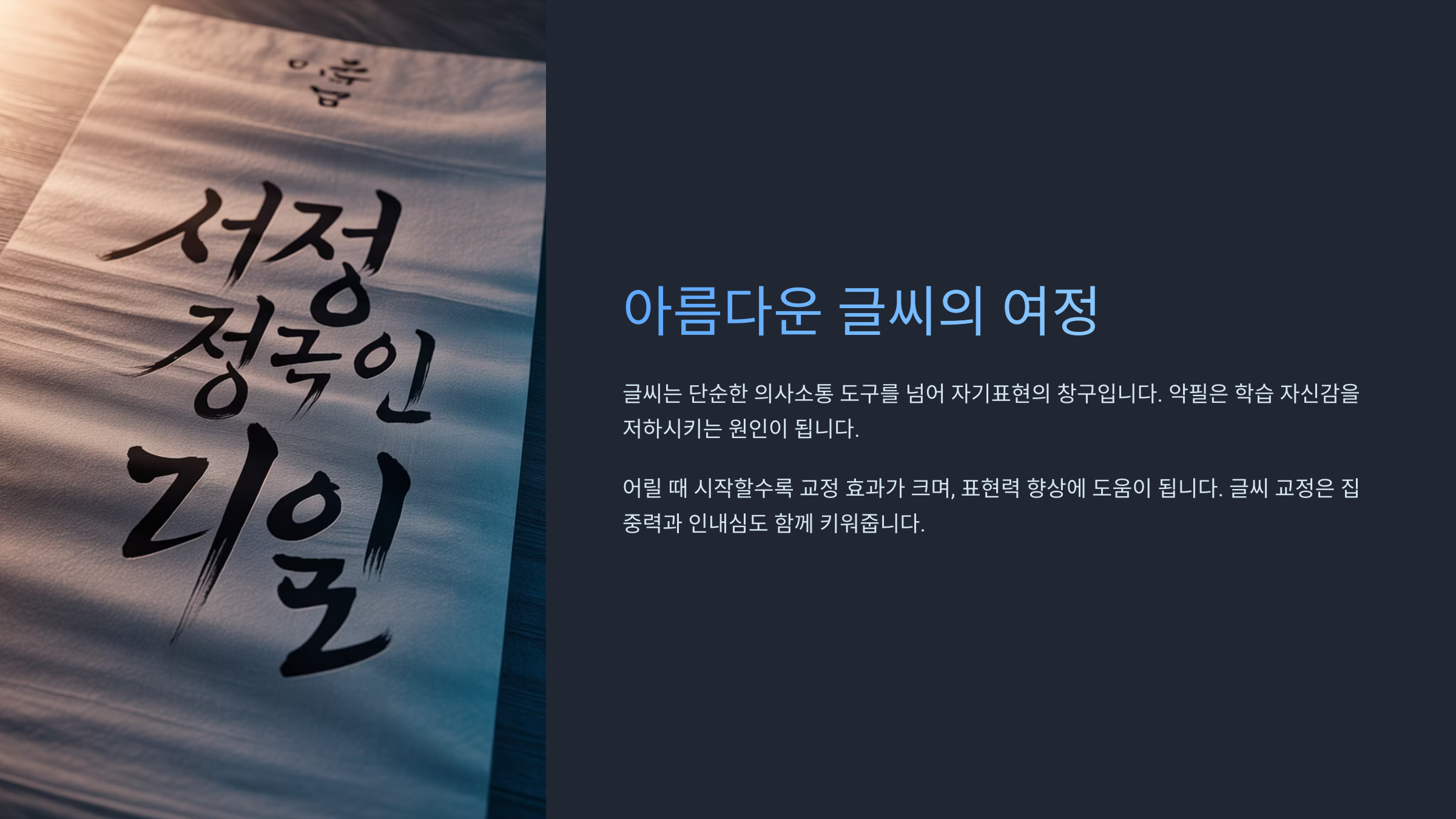
글씨 교정의 필요성과 심리
글씨는 생각보다 많은 걸 드러내는 수단이에요. 손글씨 하나만 보고도 사람의 성격이나 습관, 심지어 정서 상태를 유추하는 경우가 있거든요. 그래서인지 글씨가 예쁘지 않다고 느끼면 괜히 주눅 들고, 메모 하나 남기는 것도 불편해질 수 있어요. 저도 어릴 땐 ‘왜 내 글씨만 못생겼지?’ 하고 혼자 속상했던 기억이 나요.학교 다닐 때는 선생님들이 “글씨 좀 똑바로 써!” 하며 혼내셨던 경험도 많았고요. 하지만 아이러니하게도 글씨는 누가 정식으로 가르쳐주지 않아요. 대부분 스스로 익히고 익숙해지는 과정이라, 잘못된 습관이 들면 평생 가기도 해요. 그렇기 때문에 의식적으로 ‘교정’을 해야 변화를 느낄 수 있답니다.
글씨가 예뻐지면 얻는 가장 큰 이점 중 하나는 자신감이에요. 회의록을 손글씨로 작성하거나 누군가에게 편지를 쓸 때, 글씨가 깔끔하면 그 자체로 메시지가 더 명확하고 진정성 있게 전달돼요. 이건 단순히 미적 측면만이 아니라, '내가 내 글씨에 만족한다'는 마음이 커진다는 의미이기도 하죠.
그리고 무엇보다 중요한 건, 글씨 교정은 나이와 상관없이 누구나 시작할 수 있다는 점이에요! 초등학생이든, 직장인이든, 심지어 60대 이후의 분들도 글씨를 바꿀 수 있어요. 실제로 글씨 교정 수업을 듣는 수강생 중 상당수가 성인이라는 통계도 있답니다.
📝 연령대별 글씨 교정 동기 비교표
연령대 교정 시작 이유 선호하는 방식 10대 시험지 채점, 친구와의 메모 오프라인 수업, 필사 20~30대 자기관리, 이력서, 다이어리 온라인 클래스, 글씨 노트 40대 이상 취미생활, 자존감 회복 방문 수업, TV 강좌 이렇게 연령대마다 동기와 방법이 다르지만, 공통점은 하나예요. ‘지금보다 더 나은 나’가 되고 싶다는 마음! 그리고 그 시작이 바로 ‘글씨 교정’일 수 있다는 거죠. 📌
내가 생각했을 때, 글씨 교정은 단순히 글자를 예쁘게 쓰는 걸 넘어서 나 자신을 가꾸는 과정 같았어요. 내 손끝에서 시작되는 변화가 삶의 자신감으로 연결되더라고요.
이제 다음으로는 실제 글씨 교정이 어떻게 진행되는지, 어떤 과정이 있는지 알아볼게요. ‘어떻게 바뀔 수 있지?’ 궁금했던 분들에게 구체적인 가이드를 드릴게요 ✨
📐 교정 방법과 실제 과정
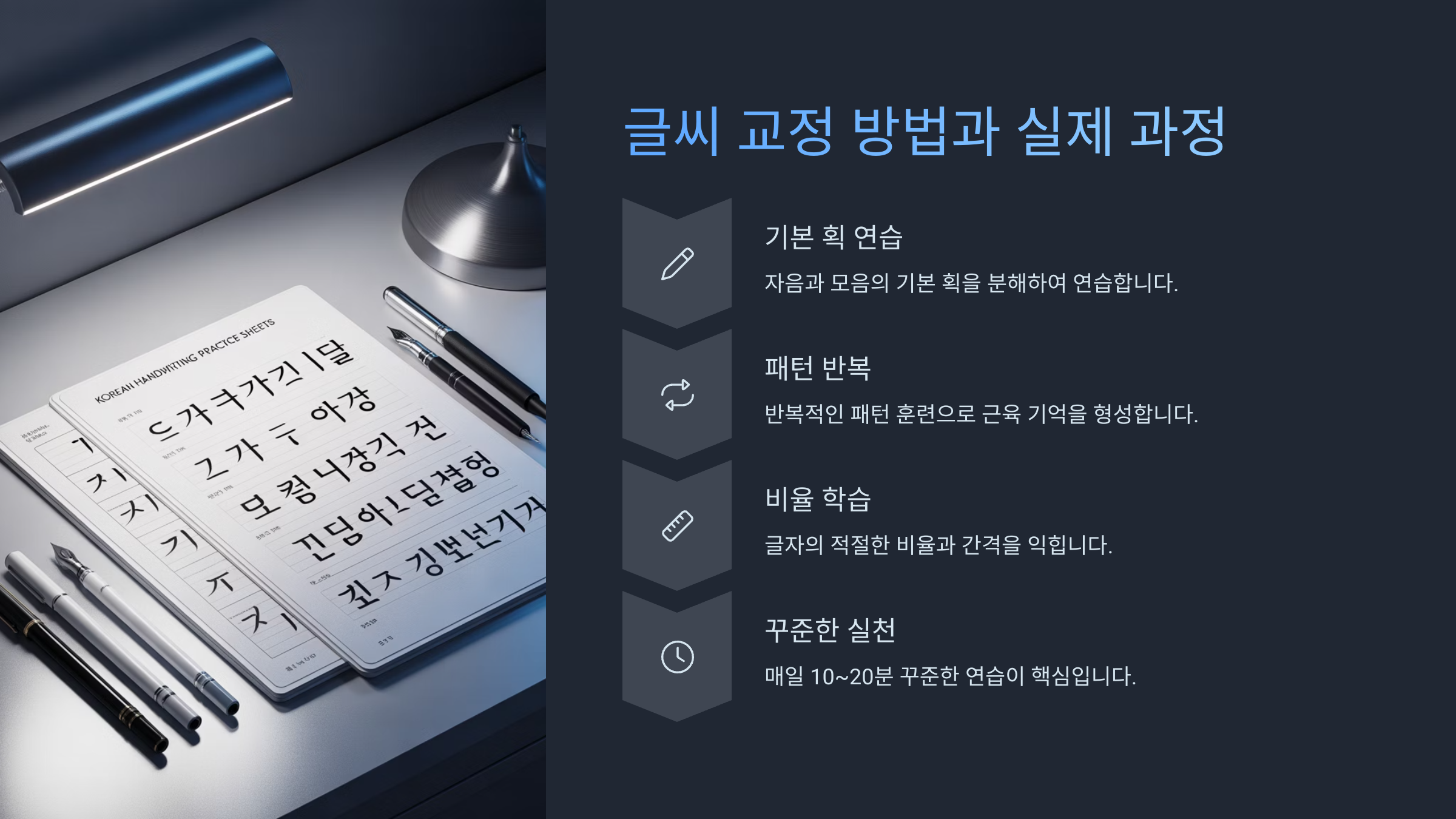
교정 방법과 실제 과정
글씨 교정은 단순히 '예쁘게 쓰기'가 아니에요. 올바른 자세와 연필 잡는 법, 획의 균형과 속도 조절까지 고려해야 하는 섬세한 과정이죠. 처음에는 생각보다 손도 아프고, 자꾸 익숙한 형태로 돌아가려는 습관 때문에 속상할 수 있어요. 하지만 이 모든 과정을 거치면 확실한 변화가 찾아온답니다!일반적으로 글씨 교정 과정은 4단계로 나눌 수 있어요. 첫 번째는 자기 글씨 분석이에요. 어떤 부분이 흐트러졌는지, 왜 그 습관이 생겼는지 전문가가 피드백을 주죠. 두 번째는 기초 선 연습! 이 부분이 지루하게 느껴지지만, 안정적인 글씨의 기본이 되는 핵심 훈련이에요.
세 번째 단계는 자주 사용하는 단어, 문장을 반복 연습하면서 실제 적용력을 키우는 거예요. 마지막 네 번째는 자기만의 스타일을 유지하면서도 보기 좋은 형태로 다듬어가는 개인화 교정 단계예요. 이쯤 되면 글씨에 자신감이 붙고, 필기 습관도 안정되기 시작해요!
요즘엔 온라인 수업이 정말 잘 되어 있어서, 교재만 있으면 집에서도 충분히 따라 할 수 있어요. 특히 줌이나 영상 강의를 통해 직접 시범을 보며 알려주는 프로그램도 많아졌고요. 다이어리 꾸미기, 캘리그라피와 함께 응용하는 것도 재미 요소 중 하나랍니다 🎨
📚 글씨 교정 4단계 요약표
단계 내용 목표 1단계 자기 글씨 분석 문제점 파악 2단계 기초 선 연습 획의 균형 훈련 3단계 단어, 문장 연습 실전 적용 4단계 개인화 교정 자기만의 스타일 완성 교정은 일정한 주기와 꾸준함이 가장 중요해요. 매일 10~20분 정도만 투자해도 2~3개월 내에 눈에 띄는 변화가 나타나거든요. 운동처럼 처음엔 힘들어도 익숙해지면 오히려 마음이 안정되기도 해요.
글씨를 교정하면서 놀라운 건 단순히 보기만 좋아지는 게 아니라, 생각이 정리되고 자신을 표현하는 힘이 생긴다는 점이에요. 한 글자 한 글자에 집중하다 보면 자신도 몰랐던 성격과 마주하게 되거든요. 글씨는 곧 마음의 모양이에요 💬
이제 다음은 정말 많은 분들이 궁금해하시는 ‘글씨 교정 전후 실제 변화’ 사례를 소개해드릴게요! 사진으로 보기 전엔 잘 몰랐던 극적인 차이, 바로 이어서 확인해보세요 👀
🔍 교정 전후 비교 리얼사례
교정 전후 비교 리얼사례
글씨 교정을 시작하기 전에는 '진짜 나도 바뀔 수 있을까?' 하는 의심이 들 수밖에 없어요. 인터넷에 떠도는 후기를 보면서도, '저건 선천적으로 손재주가 있는 사람 얘기 아냐?'라고 생각하게 되죠. 그런데 실제 교정을 받은 사람들의 전후 사진을 보면, 그런 생각이 확 사라져요! 📸예를 들어, 30대 직장인 A씨는 회사 메모를 할 때마다 글씨 때문에 스트레스를 받았어요. 알아보기 힘들 정도로 흘려쓰는 습관이 있었거든요. 하지만 8주간 주 3회 글씨 교정 수업을 듣고 나서, 메모장이 마치 인쇄한 것처럼 깔끔하게 바뀌었답니다. 동료들도 깜짝 놀랐다고 해요!
또 다른 예는 대학생 B씨예요. 졸업논문을 직접 손글씨로 정리하던 중, 지도교수님이 '글씨체 덕분에 논문이 더 정리돼 보인다'고 칭찬했어요. 처음에는 획이 무너지고 글자가 기울어져 있던 글씨가, 반복 훈련으로 안정적이고 정갈한 스타일로 바뀐 거죠. 이런 변화는 사진으로 보면 더욱 확실히 느껴져요.
이런 실전 후기들은 단순히 이론적인 효과를 넘어선, 진짜 사람들의 변화예요. 사람마다 출발선이 달라도, 공통적으로 '꾸준함'과 '피드백'을 통해 달라졌다는 점에서 희망적이죠. 그리고 이건 누구에게나 해당되는 이야기예요 😊
📷 실제 글씨 교정 사례 비교표
사례 교정 전 교정 후 소요 기간 직장인 A씨 흘려 쓰고 가독성 낮음 정갈하고 균형 잡힘 8주 대학생 B씨 획 불균형, 좌우 기울어짐 획이 균일하고 안정적 6주 주부 C씨 작고 흐릿한 글씨 크고 또렷해짐 12주 중요한 건 ‘완벽하게 잘 써야 한다’가 아니라, ‘내 글씨를 내가 좋아할 수 있는 수준’까지 가는 거예요. 그 기준은 사람마다 다르지만, 그 점을 기준으로 삼으면 교정 과정이 훨씬 즐거워진답니다 😍
글씨 교정이 이렇게 삶의 질까지 바꿀 수 있다는 걸 보면, 단순한 미용적 개선이 아니라 실질적인 생활의 변화로 연결되는 셈이에요. 다음은 '글씨'가 마음과 성격에 어떤 영향을 미치는지도 알아볼게요 🧠
🧠 글씨가 성격과 자존감에 미치는 영향
글씨가 성격과 자존감에 미치는 영향
사람의 글씨는 마음의 거울이라고도 불려요. 획의 강약, 글자의 간격, 정렬 정도에 따라 그 사람의 정서 상태나 심리적 성향을 어느 정도 짐작할 수 있기 때문이에요. 예를 들어, 글씨가 굉장히 작고 촘촘하다면 내향적이거나 조심스러운 성격일 가능성이 높고, 글씨가 크고 자유롭게 퍼져 있다면 외향적이거나 감정 표현이 풍부한 성향일 수 있어요.이런 특징 때문에 심리상담 현장에서는 글씨 분석을 참고 자료로 삼기도 해요. 특히 감정 조절이 어렵거나 스트레스가 많은 사람들의 글씨는 일정하지 않거나 왜곡된 경우가 많거든요. 그래서 글씨를 교정하면서 '안정된 필체'를 만드는 과정 자체가 마음을 정돈하는 효과를 가져올 수 있어요 🧘
또 글씨 교정을 통해 자존감이 회복되는 경우도 많아요. 반복 연습을 통해 눈에 보이는 변화가 생기면, 작은 성공이 큰 자신감으로 이어지거든요. 특히 자기 일기에 정리된 글씨로 생각을 쓰거나, 누군가에게 또박또박 쓴 편지를 전할 때의 만족감은 정말 커요. 나를 표현하는 도구가 바뀌는 건 곧 내 인식이 바뀌는 일이기도 해요.
실제로 글씨가 안정되면 말투나 사고 방식도 차분해지는 경우가 있어요. 왜냐하면 글씨를 쓸 때 자연스럽게 호흡을 조절하고 집중하기 때문이에요. 머릿속이 복잡할 때 다이어리에 또박또박 글씨를 써보면 마음이 정리되는 경험, 해본 적 있으시죠? 📓
🧩 글씨 성격 분석 요소 비교표
글씨 특징 해석되는 성향 심리적 의미 작고 촘촘함 내향적, 신중함 자기 통제력 높음 크고 넓게 씀 외향적, 감성적 자기 표현 욕구 강함 기울기 불균형 정서 불안, 우울 경향 심리적 균형 필요 이처럼 글씨는 단순히 보이는 것 이상의 정보를 담고 있어요. 우리가 습관처럼 써내려가는 글씨 속에는 지금 내 상태와 기분, 인격이 담겨 있을 수 있어요. 그래서 글씨를 다듬는 건 단순히 외모를 가꾸는 것과 같다고 볼 수도 있죠. 나를 다시 바라보고 정리하는 과정이니까요 💖
다음은 ‘혼자서도 할 수 있는 글씨 교정 팁’을 알려드릴게요! 직접 실천할 수 있는 유용한 방법들을 놓치지 마세요! ✏
✏ 혼자서도 가능한 글씨 교정 팁
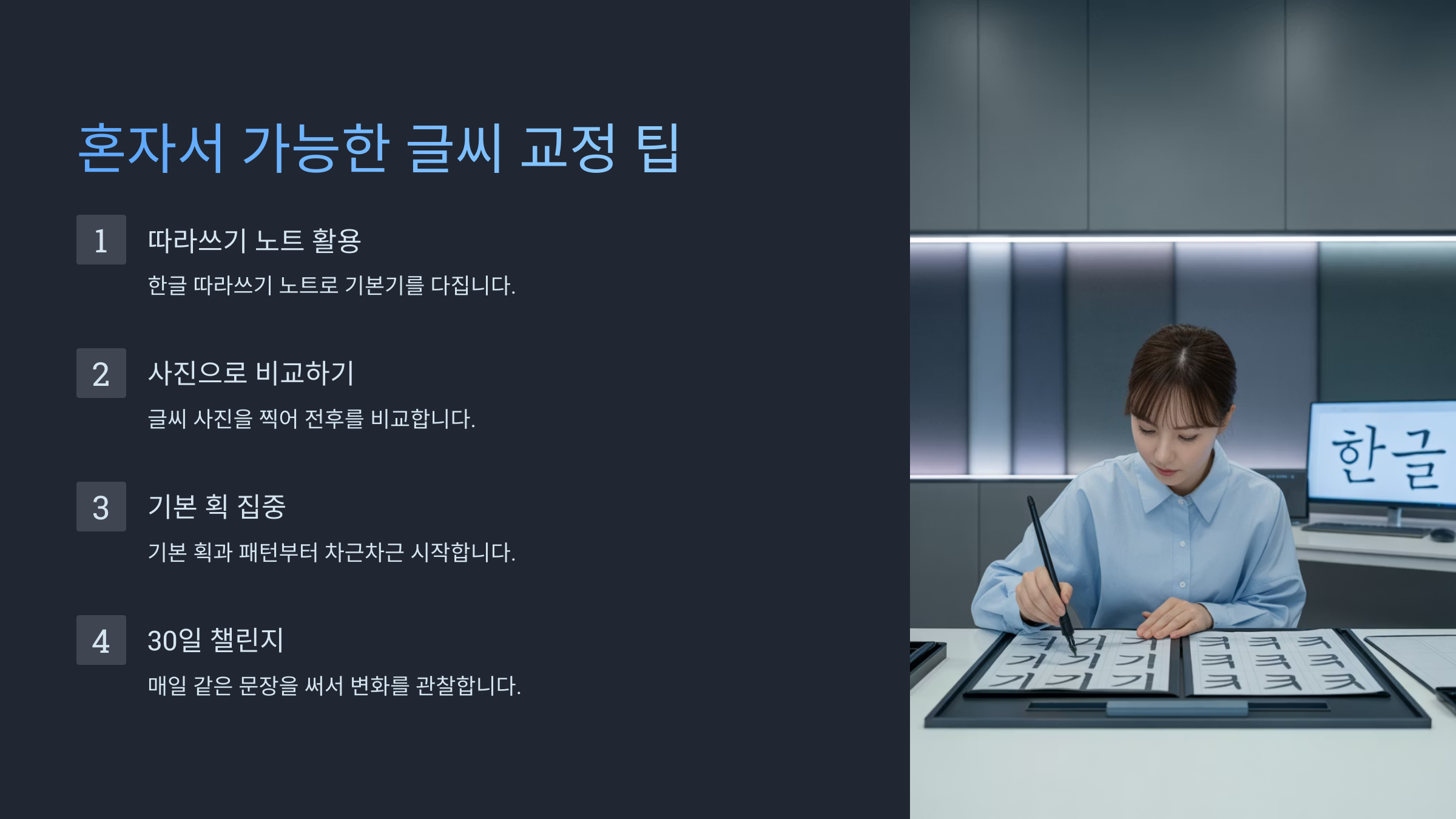
혼자서도 가능한 글씨 교정 팁
글씨 교정을 꼭 학원이나 전문가의 도움 없이도 스스로 해낼 수 있어요. 물론 처음엔 힘들 수 있지만, 꾸준함이 가장 큰 무기랍니다. 특히 바쁜 일상 속에서 시간 내기 어려운 분들에게는 ‘혼자서도 가능하다’는 점이 큰 장점이에요. 자, 그럼 집에서 바로 시작할 수 있는 팁들을 알려드릴게요! 🏠첫 번째는 기본자 필사예요. ‘가나다라마바사…’를 한 줄씩 또박또박 쓰는 훈련인데, 이 과정에서 획의 균형과 일정한 간격을 익힐 수 있어요. 처음엔 글씨의 틀만 따라 가면 되기 때문에 부담 없이 시작하기 좋아요. 특히 펜을 바꿔가며 쓰면 감각이 다르게 느껴져 효과가 더 좋답니다!
Q4. 온라인 교정 프로그램만으로 충분할까요?
A4. 충분히 가능해요. 요즘 온라인 프로그램은 피드백도 체계적이고 다양한 샘플 제공이 잘 되어 있어서 혼자 연습하기에 좋아요 🖥
Q5. 글씨가 잘 써지지 않는 날도 있는데, 어떻게 해야 하나요?
A5. 그런 날은 스트레칭이나 손 풀기 운동을 먼저 해보세요. 손이 뻣뻣하면 글씨도 잘 안 나와요. 부담 없이 필사만 가볍게 해도 좋아요 👐
Q6. 나만의 글씨체를 갖고 싶은데, 교정 후에도 가능할까요?
A6. 물론이에요! 교정은 ‘기본기’를 다지는 과정이에요. 그 후에는 본인의 개성을 반영한 손글씨로 발전시킬 수 있어요 🎨
Q7. 하루에 얼마나 연습하는 게 적당할까요?
A7. 10분~20분 사이면 충분해요. 중요한 건 ‘매일 꾸준히’라는 점이에요. 짧아도 자주 하는 게 더 효과적이랍니다 🔁
Q8. 글씨 교정으로 정말 성격도 바뀔 수 있나요?
A8. 직접적인 변화보다는 ‘자기 인식’이 바뀌어요. 글씨에 대한 만족감이 생기면 자신감도 커지고, 표현력이 풍부해져요 💬